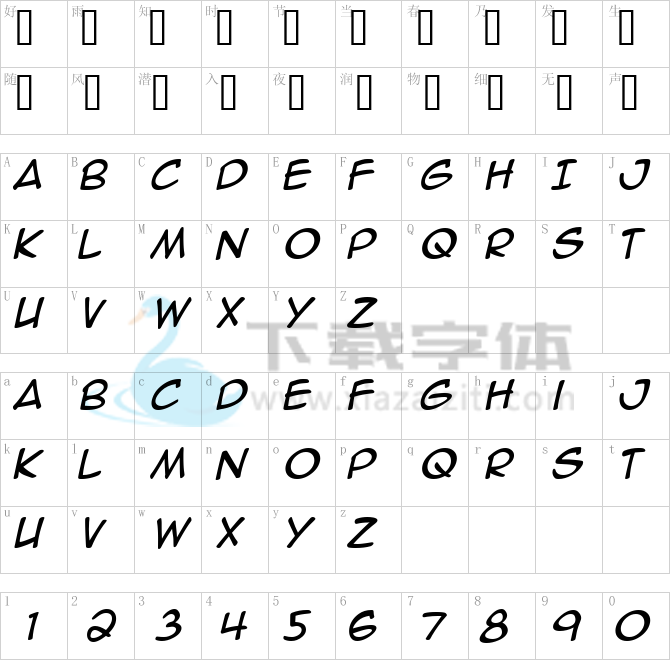
Anime Ace.ttf字体下载,这款字体结构工整、笔画清晰,兼顾美观与易读性,适用于标题、正文、海报、包装、LOGO 等多种场景。字形优雅稳定,风格百搭耐看,适配日常排版与创意设计,让文字呈现更舒适、更具质感。Anime Ace.ttf字体下载一笔一画,皆是细节,以均衡的比例、流畅的线条打造舒适视觉体验,字形端正大气,风格简约现代。无论是商业设计、品牌宣传还是日常排版,都能轻松驾驭,让文字更有格调与力量。Anime Ace.ttf字体下载字体下载。